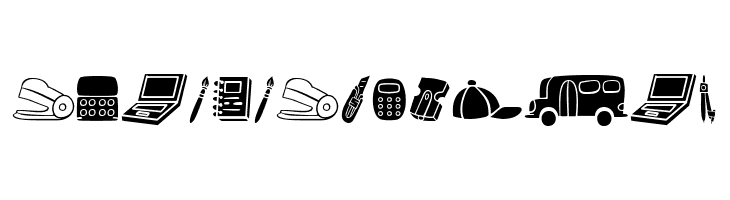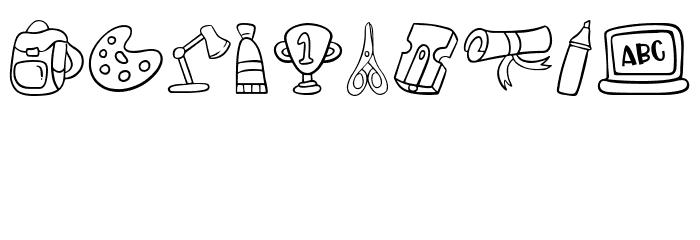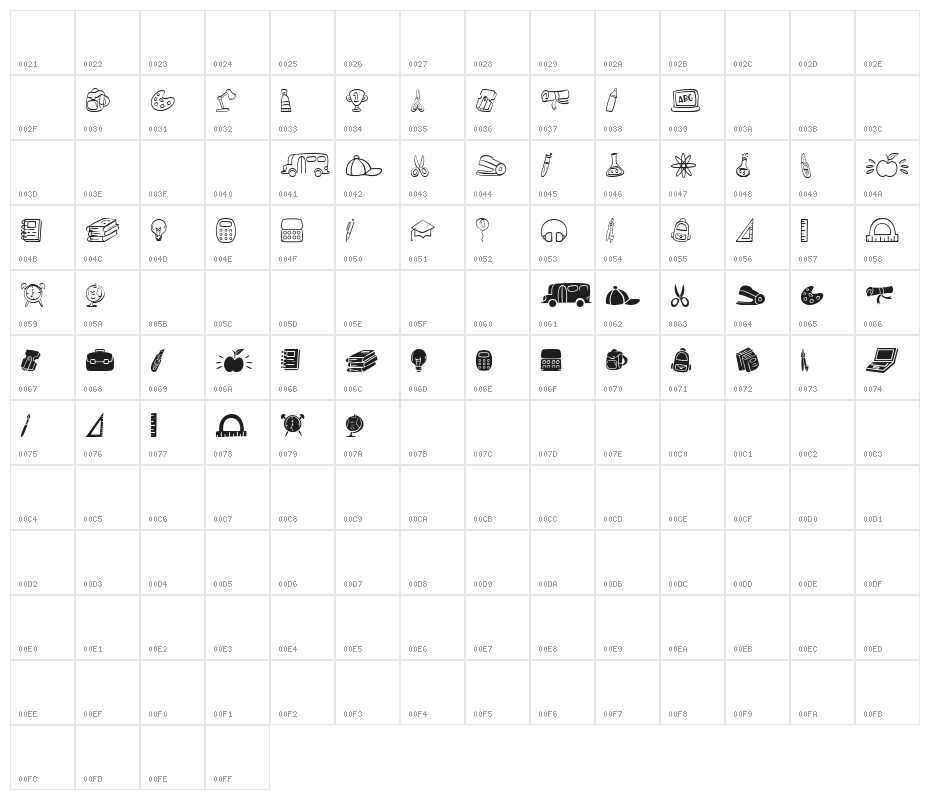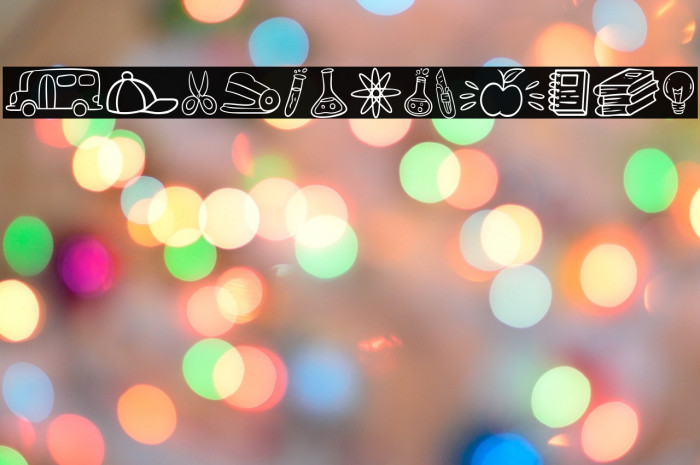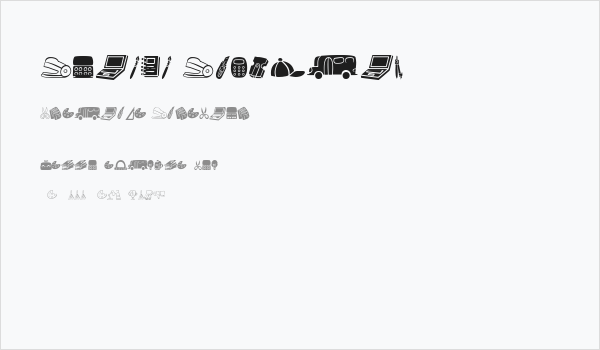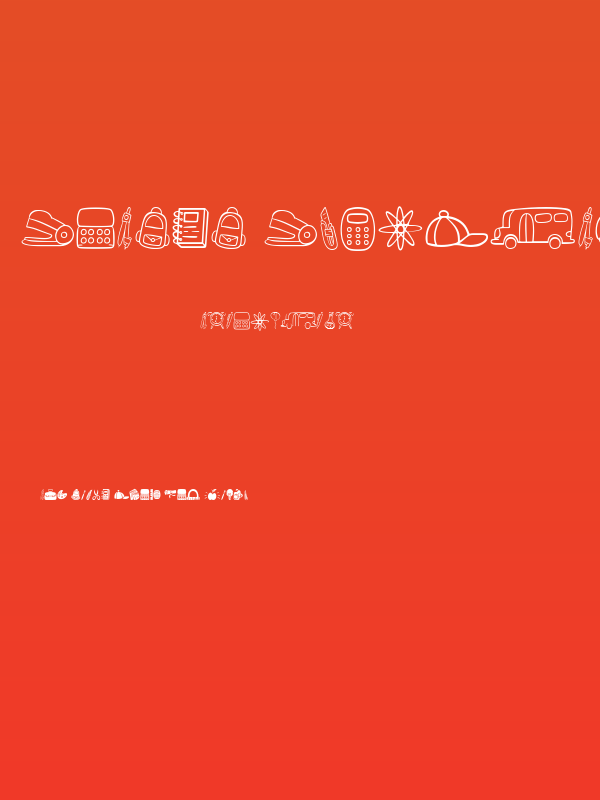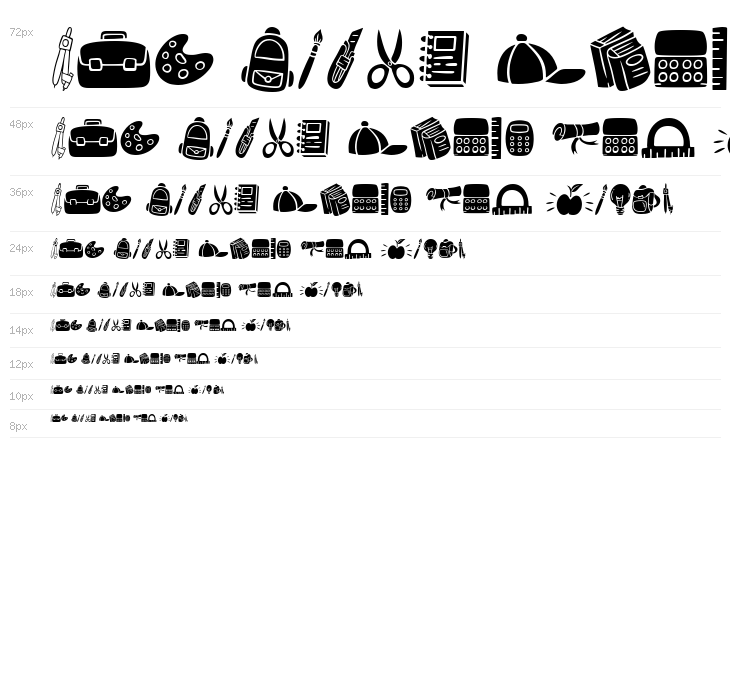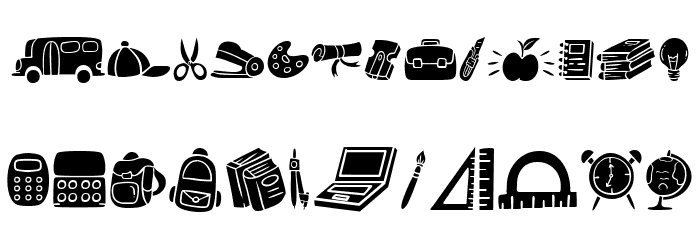
Dotuku Dingbats Font
✎ Cartoon
| 整体风格 | Playful, Educational |
| 使用场景 | Icons, Educational materials, Stationery |
| 推荐项目 | Ideal for educational materials, children's books, school-themed graphics, and playful stationery designs. |